Font chữ mảnh, với những nét chữ thanh thoát và tinh tế, đã trở thành một trong những lựa chọn hàng đầu của các nhà thiết kế đồ họa. Với vẻ đẹp thanh lịch và sang trọng, font chữ mảnh mang đến một hơi thở mới mẻ cho các thiết kế, từ logo, poster đến ấn phẩm. Bài viết này sẽ giúp bạn hiểu rõ hơn về font chữ mảnh, cách sử dụng hiệu quả và những ứng dụng của nó trong thiết kế.
Font chữ nét mảnh là loại font có các ký tự được thiết kế với các đường nét thanh mảnh, gọn gàng. Các nét chữ này thường không đậm hoặc quá nặng nề, mang lại cảm giác nhẹ nhàng, tinh tế và hiện đại. Font chữ mảnh thường được sử dụng trong các thiết kế tối giản, nơi mà sự thanh thoát và tinh tế là yếu tố quan trọng.
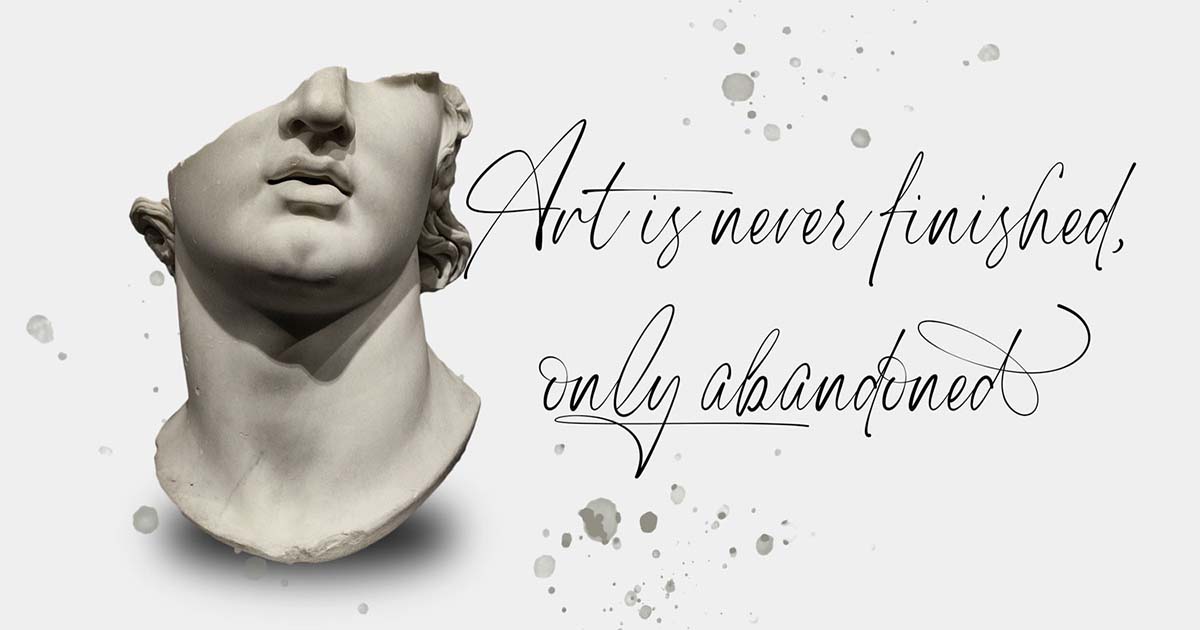
Nét chữ thanh thoát, mỏng: Đây là đặc điểm dễ nhận thấy nhất. Các nét chữ thường được tinh giản tối đa, tạo cảm giác nhẹ nhàng và thanh lịch. Điều này giúp tạo cảm giác gọn gàng, nhẹ nhàng cho văn bản, làm nổi bật nội dung mà không tạo cảm giác nặng nề.
Tỷ lệ chữ cái cân đối: Các chữ cái trong font chữ mảnh thường có tỷ lệ cân đối, hài hòa, tạo nên sự thống nhất trong thiết kế.
Khoảng cách giữa các chữ cái: Khoảng cách giữa các chữ cái thường được điều chỉnh hợp lý, tạo cảm giác thông thoáng và dễ đọc.
Độ tương phản cao :.Dù các nét chữ rất mỏng, nhưng nếu được sử dụng hợp lý, font chữ mảnh vẫn đảm bảo tính dễ đọc, đặc biệt khi sử dụng ở kích thước lớn hoặc trên nền có độ tương phản cao.
Phong cách đa dạng: Font chữ mảnh có rất nhiều phong cách khác nhau, từ cổ điển đến hiện đại, từ đơn giản đến cầu kỳ.
Hiện nay, có rất nhiều loại font chữ mảnh khác nhau, từ serif đến sans-serif, giúp bạn dễ dàng lựa chọn phù hợp với mục đích thiết kế của mình. Dưới đây là một số loại font chữ mảnh phổ biến:
Font serif mảnh: Là loại font chữ mảnh có các đường nét chân ở cuối chữ. Chúng thường mang đến cảm giác truyền thống và cổ điển hơn.
Font sans serif mảnh: Không có các đường nét chân, tạo cảm giác hiện đại và đơn giản.
Font script mảnh: Là loại font chữ viết tay, có nét chữ uốn lượn mềm mại, tạo cảm giác nữ tính và lãng mạn.
Dưới đây là 15 font chữ nét mảnh đang được tải và dùng nhiều nhất
1. Font TH Omed Brush | Link tải
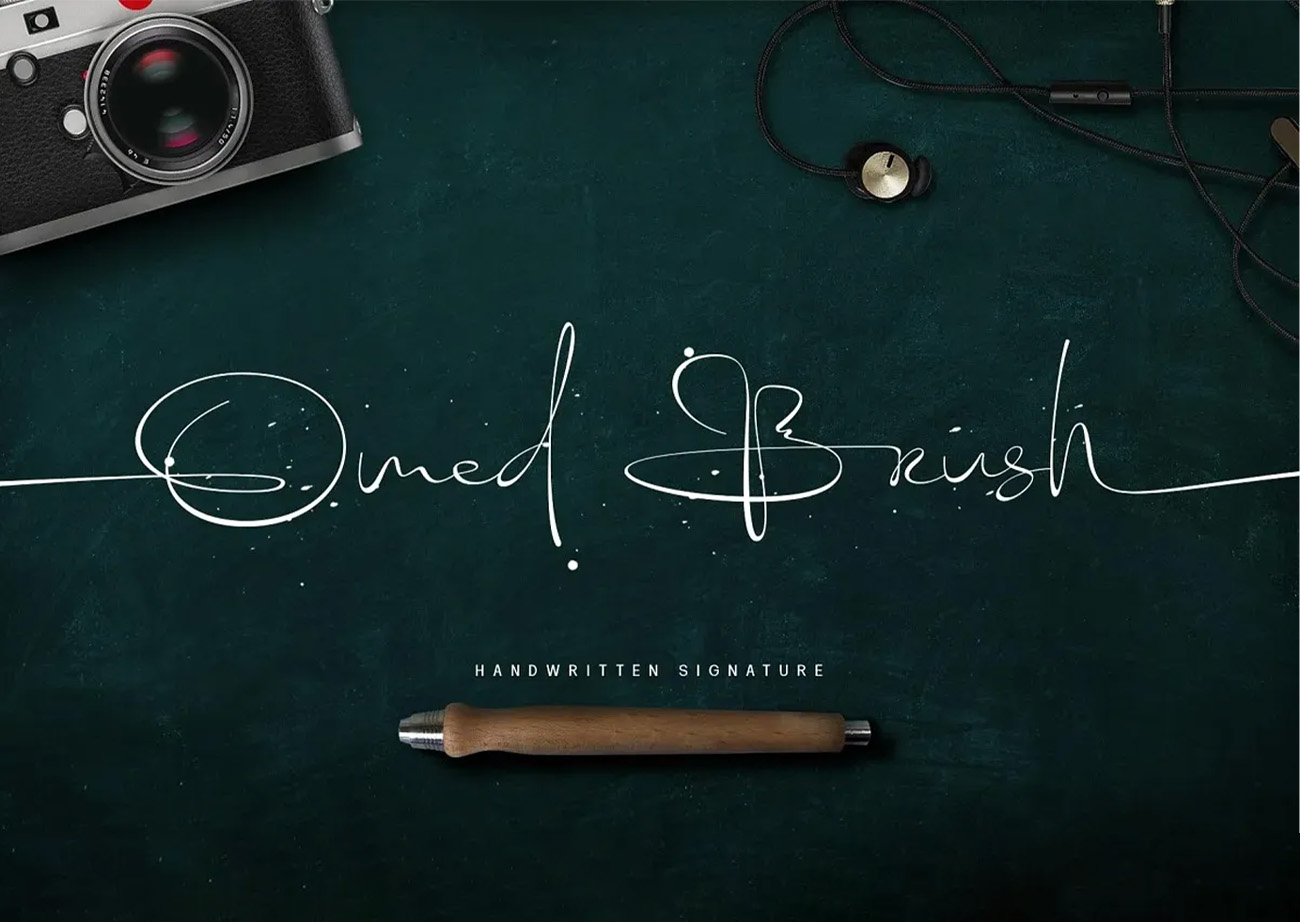
2. Font chữ TH Jalliya Việt Hoá | Link tải
3. Font chữ việt hóa TH Maginia | Link tải
4. Font chữ TH Frenchasette Việt Hoá | Link tải
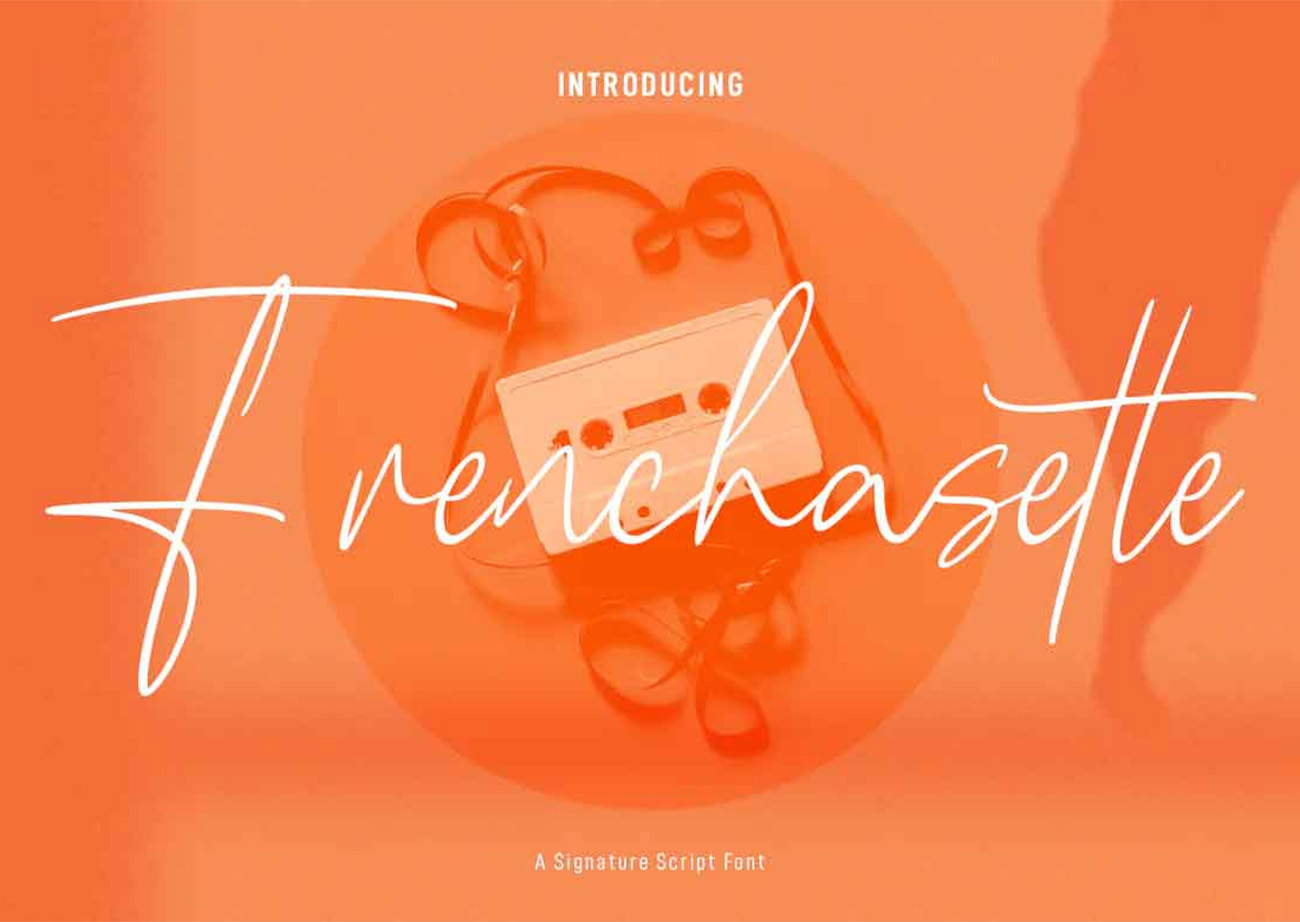
5. Font chữ TH Migratory | Link tải
6. Font chữ TH Manchester | Link tải
7. Font chữ TH Mrattoos-Regular | Link tải
8. Font chữ TH Wellyon-Regular | Link tải
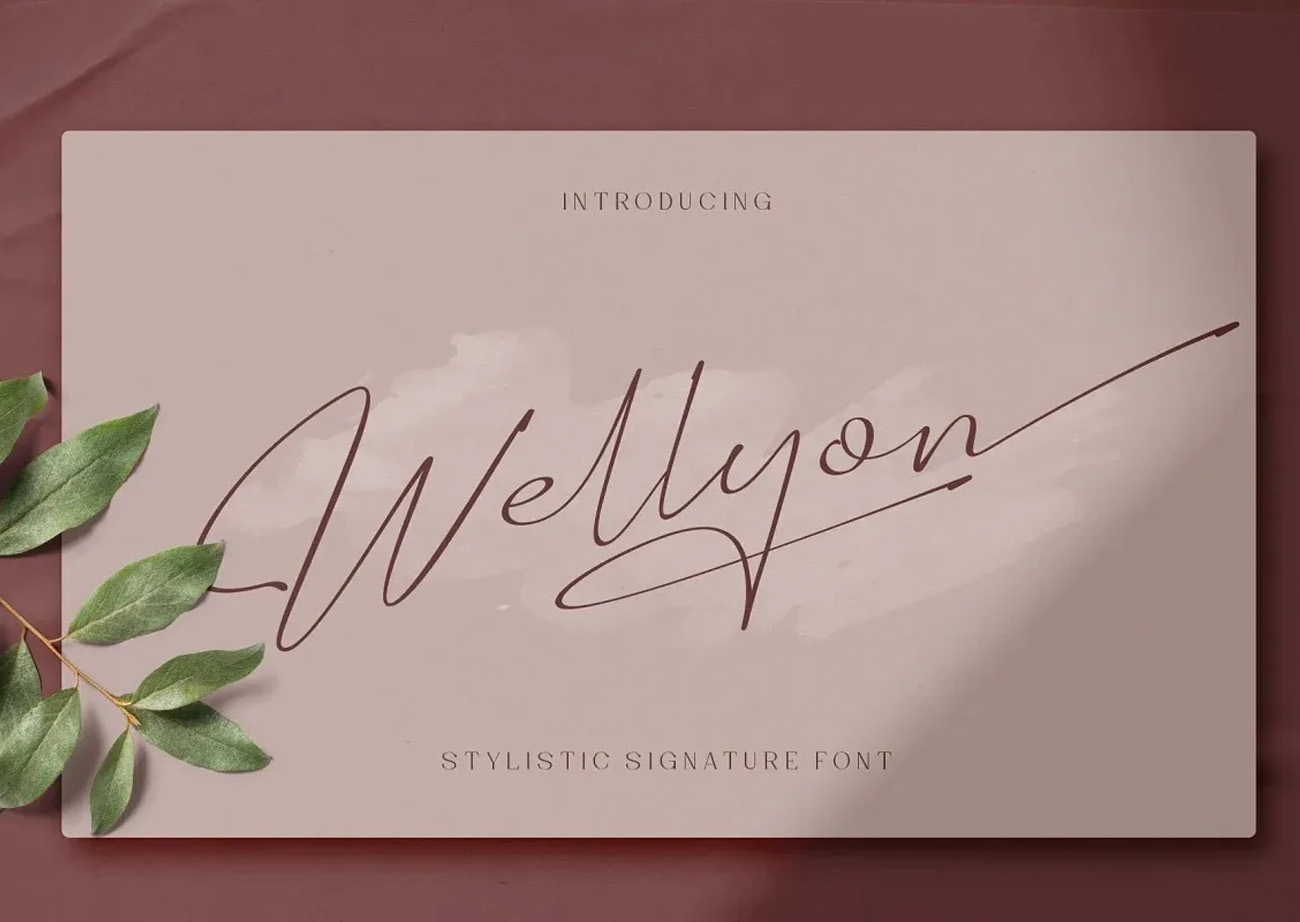
9. Font chữ TH Qara | Link tải
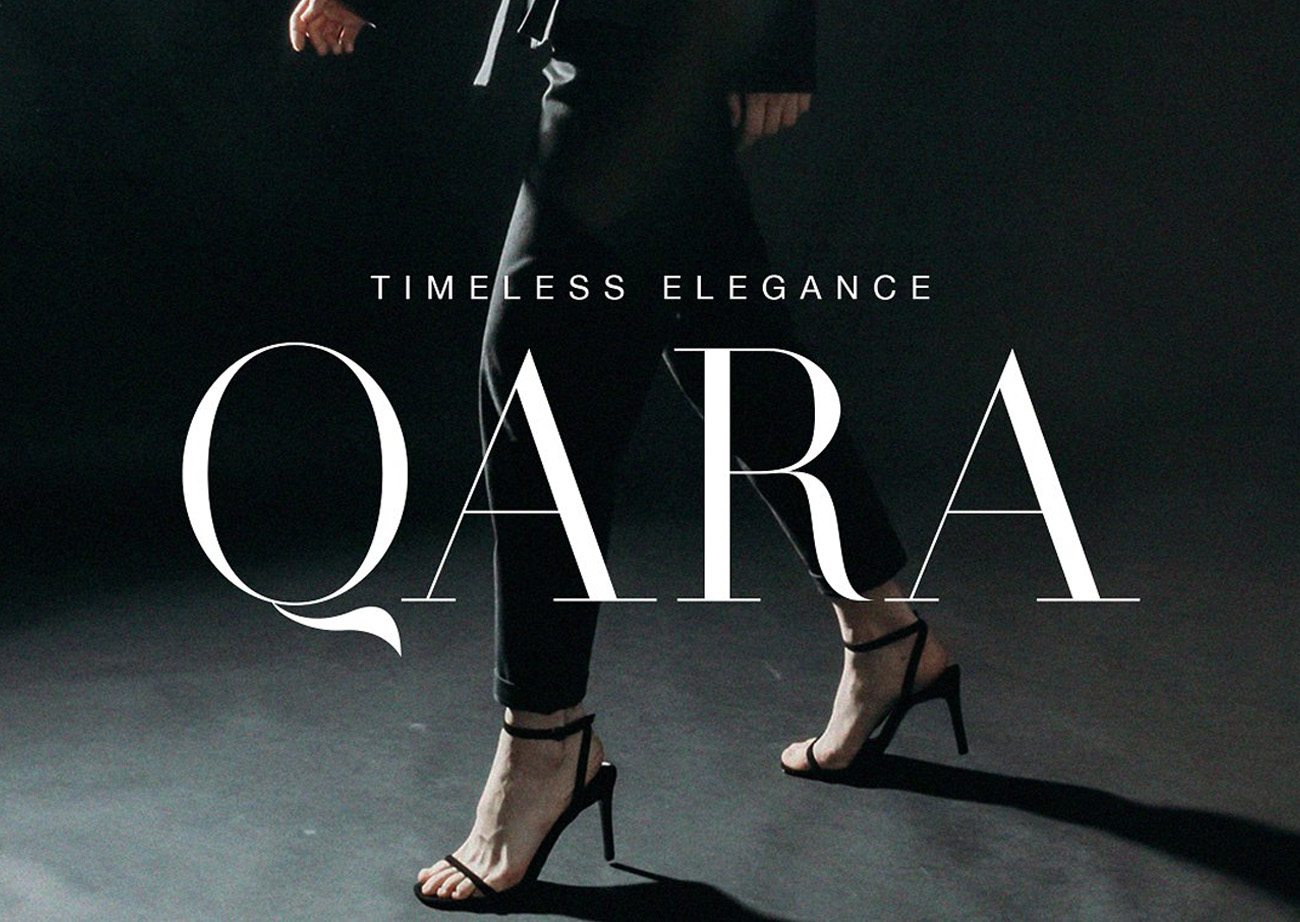
10. Font chữ TH Romusa | Link tải
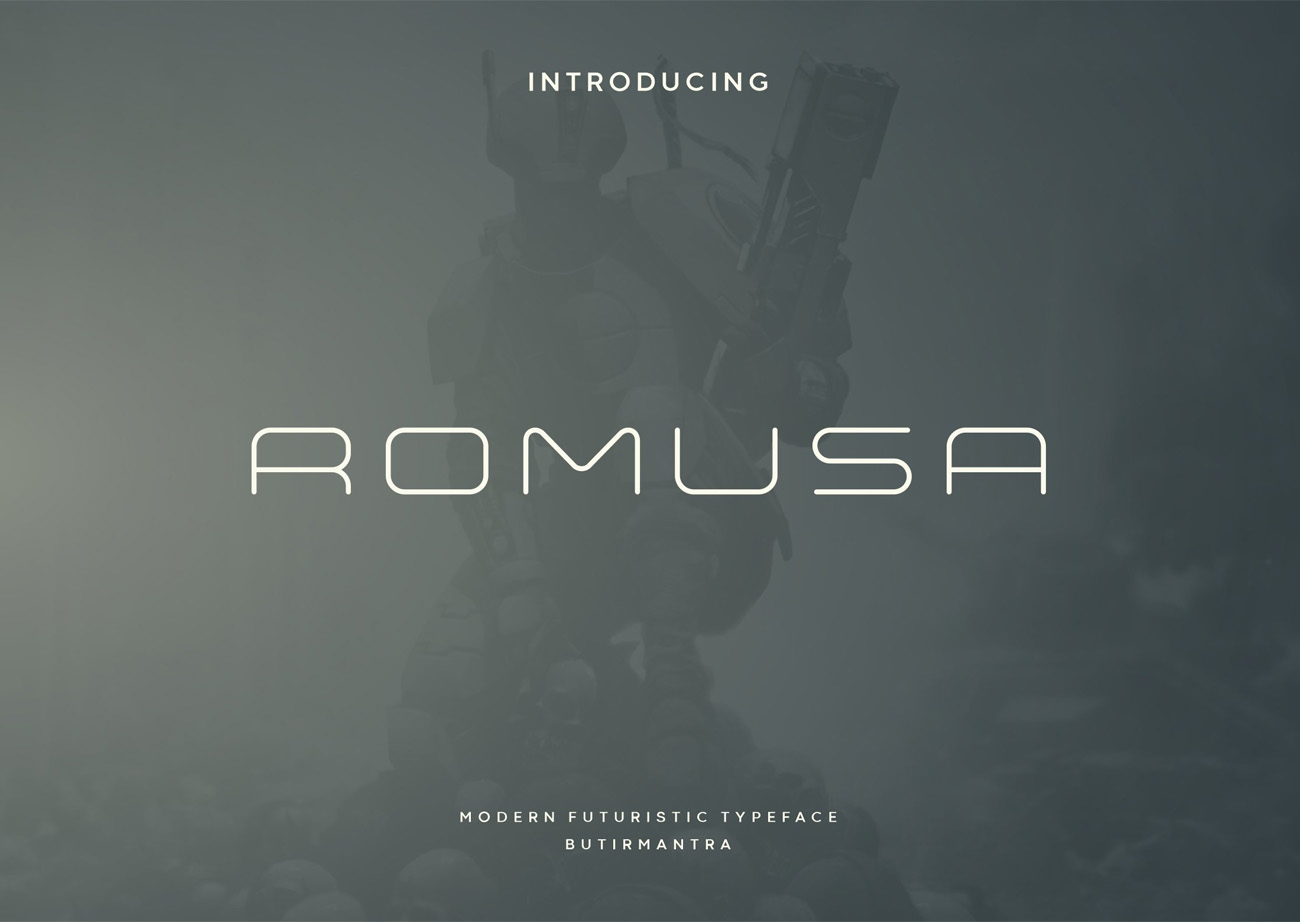
11. Font chữ TH Billistone | Link tải
12. Font chữ TH Alessa Beilaire Deluxe | Link tải
13. Font chữ TH Bird House Script | Link tải
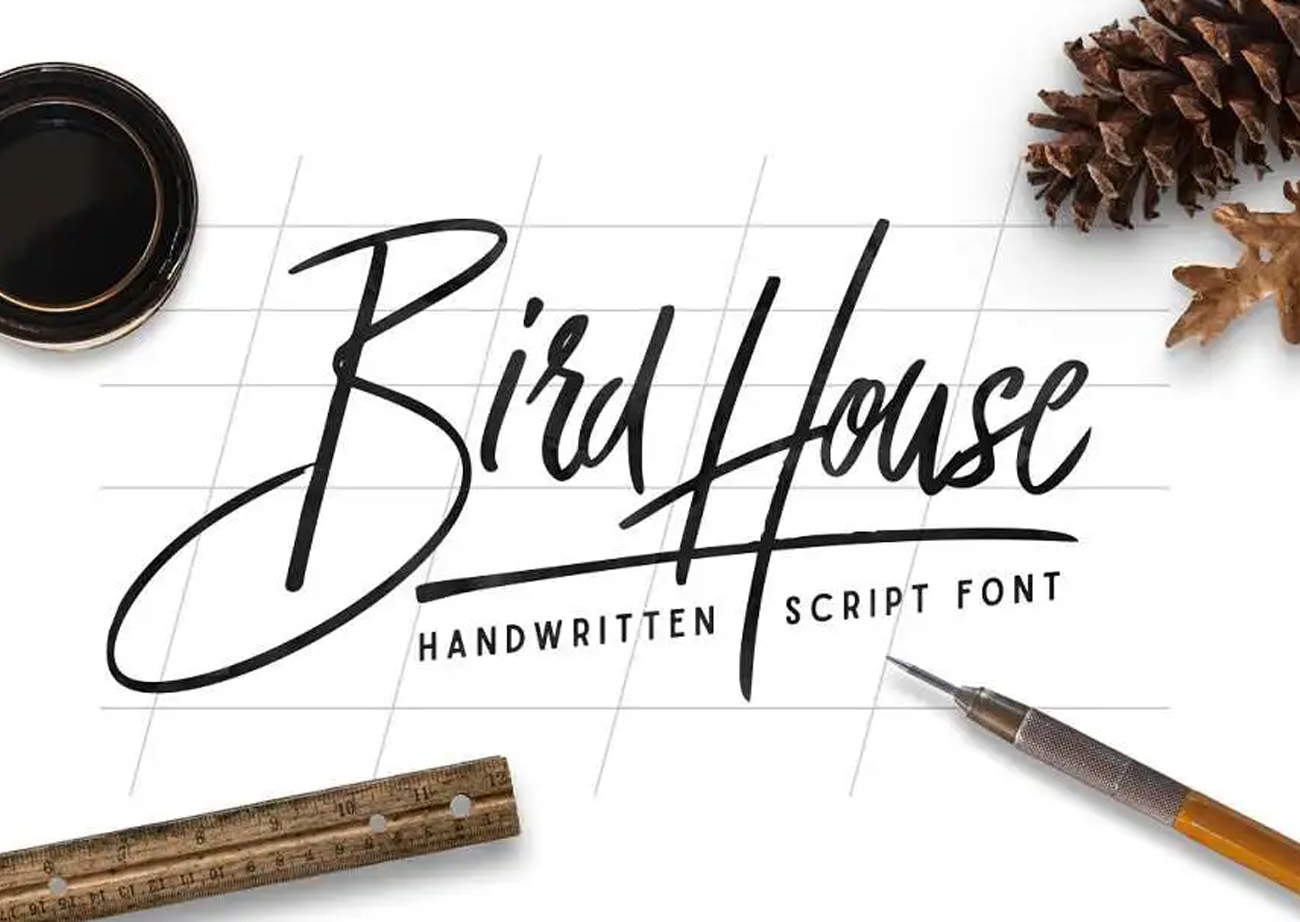
14. Font chữ TH Boulderstone Việt hóa | Link tải
15. Font chữ Jhodes Việt Hóa | Link tải
Tạo ấn tượng cao cấp: Font chữ nét mảnh giúp logo trở nên thanh lịch, sang trọng, phù hợp với các thương hiệu cao cấp.
Truyền tải thông điệp tinh tế: Font chữ mảnh giúp truyền tải những thông điệp tinh tế, nhẹ nhàng về sản phẩm hoặc dịch vụ.
Ví dụ: Các thương hiệu thời trang cao cấp, mỹ phẩm, đồ trang sức thường sử dụng font chữ mảnh cho logo của mình để tạo ấn tượng về sự thanh lịch và chuyên nghiệp.
Tạo điểm nhấn: Font chữ mảnh giúp nổi bật thông điệp chính trên poster, banner.
Thu hút sự chú ý: Với vẻ đẹp thanh lịch, font chữ mảnh dễ dàng thu hút ánh nhìn của người xem.
Phù hợp với nhiều sự kiện: Từ các sự kiện cao cấp đến các sự kiện văn hóa, nghệ thuật.
posters and banners using thin fonts
Tăng tính chuyên nghiệp: Font chữ mảnh giúp tài liệu trở nên chuyên nghiệp và ấn tượng hơn.
Dễ đọc: Khi được sử dụng đúng cách, font chữ mảnh vẫn đảm bảo tính dễ đọc.
Phù hợp với nhiều loại tài liệu: Báo cáo, thuyết trình, tài liệu marketing...
Tạo điểm nhấn: Font chữ mảnh thường được sử dụng trong thiết kế bao bì sản phẩm, đặc biệt là những sản phẩm cao cấp như mỹ phẩm, đồ uống, hay quà tặng. Font chữ nét mảnh sản tạo điểm nhấn cho sản phẩm của bạn
Truyền tải thông điệp về sản phẩm: Font chữ mảnh có thể giúp truyền tải thông điệp về chất lượng, sự tinh tế của sản phẩm.
Phù hợp với nhiều loại sản phẩm: Mỹ phẩm, thực phẩm cao cấp, đồ uống, quà tặng sang trọng..
Tạo ấn tượng: Font chữ mảnh giúp các ấn phẩm như danh thiếp, tờ rơi, brochure trở nên sang trọng và chuyên nghiệp hơn. Với tính chất thanh thoát, font chữ mảnh giúp làm nổi bật thông điệp mà không gây rối mắt cho người xem.
Phù hợp với nhiều loại ấn phẩm: Từ ấn phẩm quảng cáo đến ấn phẩm nội bộ.Các chiến dịch quảng cáo muốn truyền tải sự sang trọng, hiện đại thường sử dụng font chữ mảnh để tạo ấn tượng tinh tế. Font chữ nét mảnh giúp brochure và catalogue trở nên thanh lịch và dễ đọc, đặc biệt khi kết hợp với hình ảnh sản phẩm.
Tổng kết
Font chữ mảnh là một công cụ thiết kế vô cùng hữu ích, giúp bạn tạo ra những tác phẩm đẹp mắt và chuyên nghiệp. Tuy nhiên, để sử dụng font chữ mảnh một cách hiệu quả, bạn cần hiểu rõ về các đặc điểm và nguyên tắc sử dụng của font